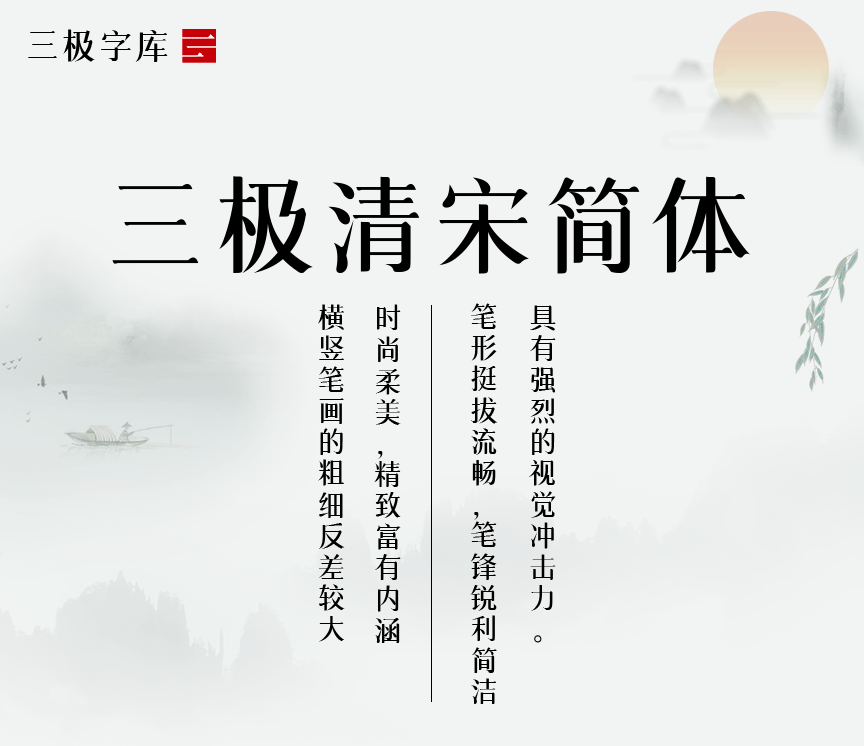
三极清宋简体家族
字体名称:三极清宋简体-纤
设计师:王荣诚,蔡建文,夏桑霜
所属分类:宋体
三极清宋简体是一款家族字体,其字形清新,布白均匀,字形结构饱满匀称、柔美,中宫偏大,笔形挺拔流畅,笔锋锐利简洁。撇、捺起笔收笔统一,个性鲜明,富有朝气。这款字的整体风格清新醒目、时尚柔美,精致富有内涵。横竖笔画的粗细反差较大,具有强烈的视觉冲击力。不但适用于各类传统纸媒,还可直接用于屏幕阅读。适用于传统印刷媒介的标题与正文排版。以及广告、标志和产品包装设计。
适用媒介:报纸、杂志、书籍、广告、标志、宣传册、空间导视、包装、屏幕显示。